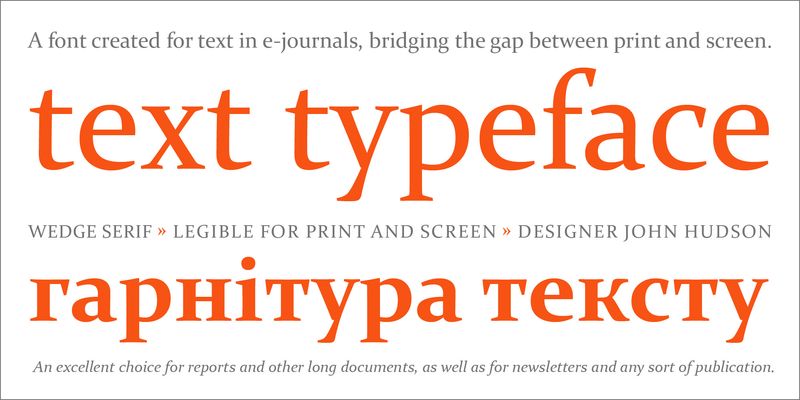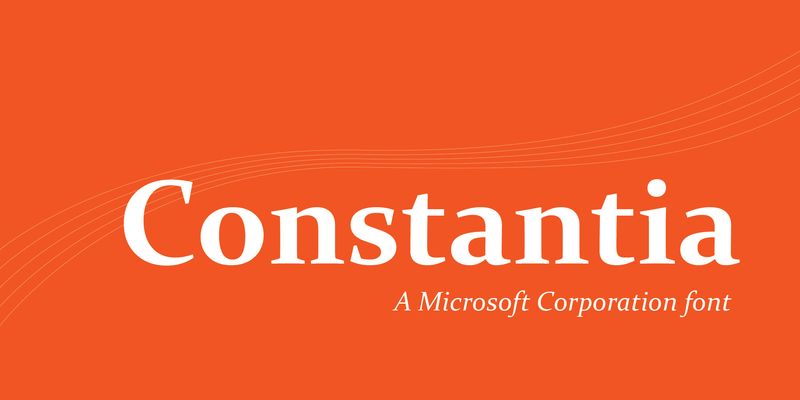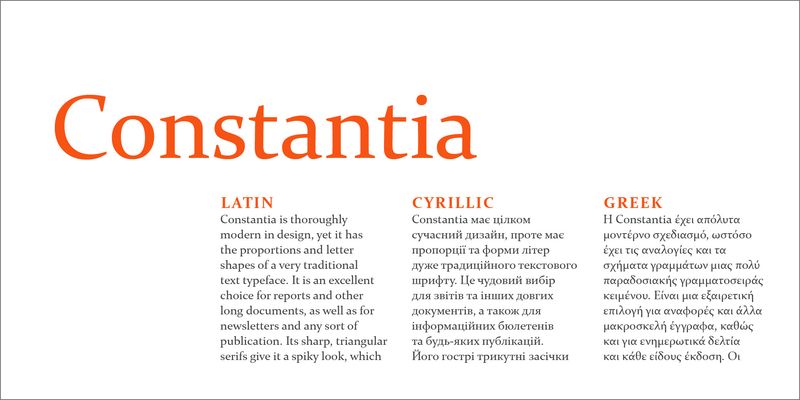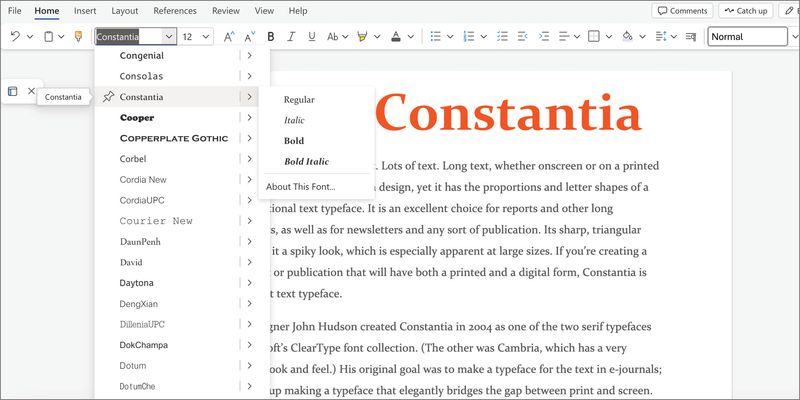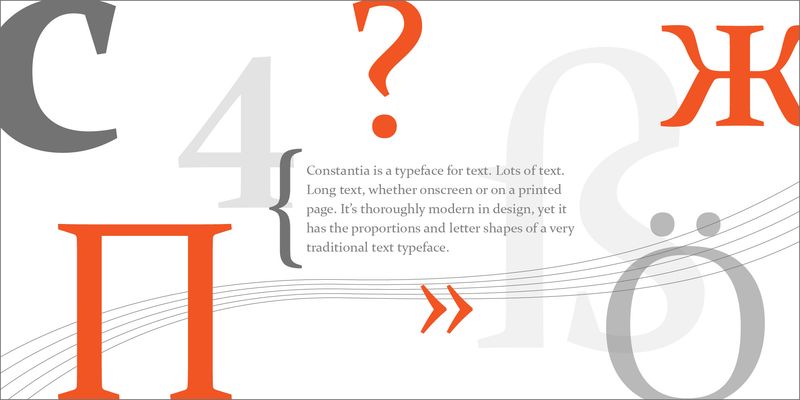
Constantia は本文用の書体です。大量の本文や、スクリーン上でも印刷物でも、長い本文用にデザインされました。完全にモダンなデザインですが、非常に伝統的な本文用書体の比率と文字の形状を備えています。レポートやその他の長い文書、ニュースレターやあらゆる種類の出版物に最適です。シャープな三角形のセリフにより、するどい見た目になり、特に大きなサイズではその印象が顕著になります。印刷とデジタルの両方の形式を持つ文書や出版物を作成する場合、Constantia は理想的な本文用書体です。
書体デザイナーの John Hudson は、2004 年に Microsoft の ClearType フォントコレクションの 2 つのセリフ書体 1 つとして Constantia を作成しました。(もう 1 つは Cambria で、見た目も雰囲気も全く違います。) 彼の当初の目標は、電子ジャーナルの本文用の書体を作ることでしたが、最終的には印刷物とスクリーンの両方に適したエレガントな書体をデザインすることに成功しました。